Et-Zeichen (&)
Im dspr. Raum ist das &-Zeichen (et-Zeichen) eine Ligatur bzw. Buchstabenverbindung, welche primär als Ersatzzeichen für das »Kaufmanns-Und« verwendet wird, bspw. »Hinz & Kunz AG« anstelle von »Hinz und Kunz AG«.
In der deutschen Sprache wird »&« als »und« gesprochen, die Ligatur selbst als »&-Zeichen« bezeichnet, was als »et-Zeichen« gesprochen wird; ugs. auch als »Und-Zeichen« tituliert. In der Typografie zählt das &-Zeichen zu den Wortligaturen; eng. »Ampersand«.
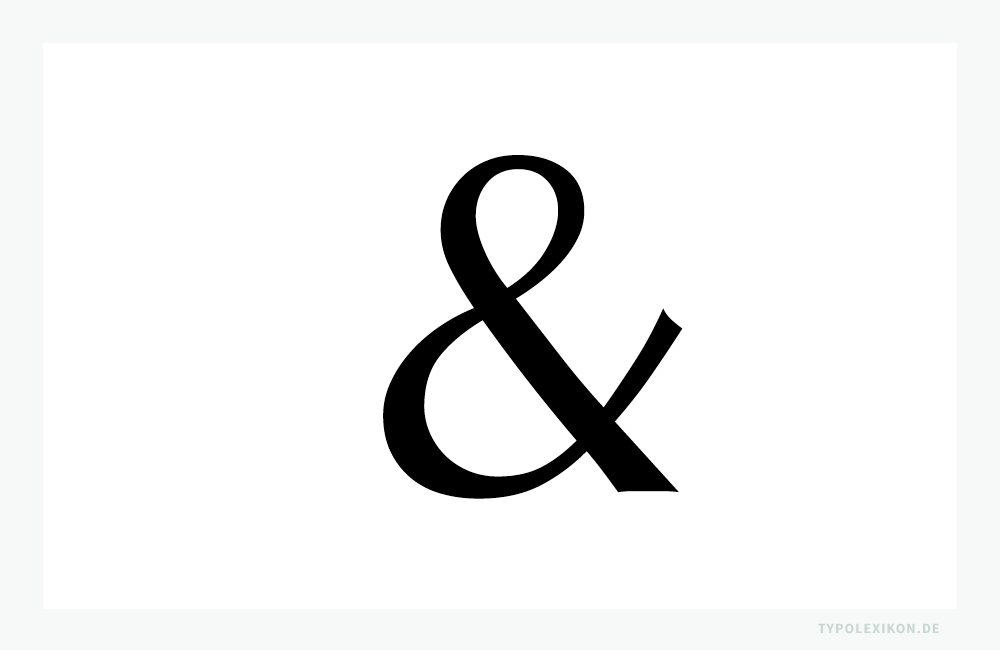
Da das &-Zeichen in der dt. Schriftsprache – im Gegensatz zur eng. 1) oder frz. 2) 3) 4) – nicht als grammatikalische Konjunktion (z.B. aber, denn, oder, und), sondern nur als Bindewort in Firmierungen (offiziell nur bei Firmendoppelnamen mit Eintrag ins Handelsregister) oder in der besonderen Rechtsform der Kommanditgesellschaft (KG) – der GmbH & Co. KG – verwendet wird, 5) wird es ab dem späten 19. Jh. auch als »kaufmännisches Und-Zeichen«, »Kaufmanns-Und«, »kaufmännisches Und« oder »Firmen-Und« bezeichnet. Das »&« sollte nicht mit der Kaufmannsligatur »@« (at-Zeichen) oder dem »+« (Pluszeichen) verwechselt werden.
Ursprung
Das &-Zeichen ist eine Buchstabenverschmelzung aus den Minuskeln »e« und »t«. Etymologisch rührt diese aus der lt. Konjunktion »et« für dt. »und«, »und tatsächlich«, »auch«.
Vermutlich entstand die &-Ligatur in ihrer heutigen Antiqua-Form als kalligrafische Abbreviatur mit den Minuskeln karolingischen (Karolingischen Minuskel) und humanistischen (Humanistica) Ursprungs, wobei die Epigraphik, die Paläografie und die Diplomatik bereits in vorrömischen Alphabeten erste Zeugnisse von Ligaturen und Abbreviaturen (Abkürzungen) dokumentieren.
In der Kalligrafie erfüllten Ligaturen bzw. Abbreviaturen primär die Aufgabe, schnell und ökonomisch zu schreiben, da u.a. Trägermaterialien wie Pergament bzw. später Papier sehr rar und kostbar waren. Sprachliche oder formale Aspekte kamen erst später hinzu (11./12. Jahrhundert). Ästhetische Aspekte in der Formgebung und Anwendung erst nach dem Manierismus. 6)
Generell ist es sehr schwer festzustellen, ob und ab wann eine Ligatur als originär oder als zusammengesetzt betrachtet werden muss. Das gilt auch für das &-Zeichen. Insbesondere, da in der europäischen Kalligrafie Ligaturen spätestens seit dem 1. Jahrhundert – z.B. in Form unterschiedlicher et-Zeichen – genutzt werden. Zu den ältesten noch angewandten Abbreviaturen zählt das et-Zeichen aus dem Zeichenrepertoire der Tironischen Noten von Marcus Tullius Tiro (um 103–4 v.Chr.), welches auch heute noch in Irland in unveränderter Form genutzt wird.
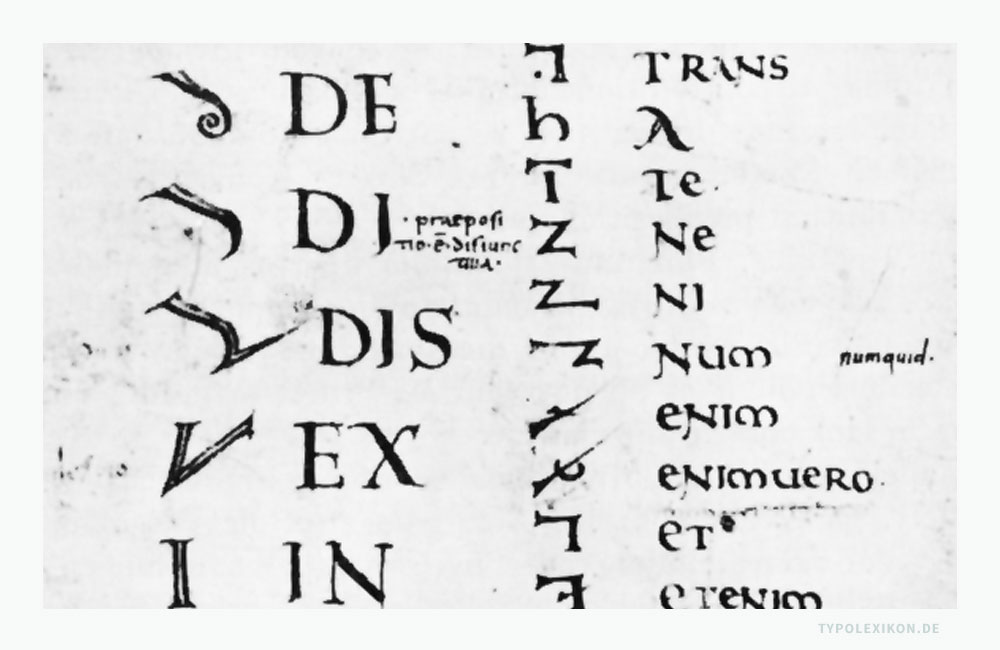
»Das &-Zeichen fast so alt wie die römische Schrift. Zwar kommt ein &-Zeichen weder in den altrömischen Inschriften noch in den monumentalen Majuskelhandschriften der Römer vor. Aber bereits 79 nach Christus begegnen wir in den flüchtigeren »graffiti«, schnell hingekratzten Inschriften, einer Ligatur et, die vielleicht als Urahn der et-Sippe angesprochen werden darf.«
In der dt. Fraktur-Typografie war das &-Zeichen über Jahrhunderte nicht üblich. Erst im Laufe der prosperierenden Industrialisierung und insbesondere mit Gebrauch von Antiqua-Druckschriften wurde das &-Zeichen ab dem späten 19. Jahrhundert als »ligaturische Abbreviatur« in Firmendoppelnamen – sowohl im Druckwesen als auch in der Schildermalerei – verwendet.
Orthographische Regeln
Die deutsche (und österreichische) Orthografie kennt – abgesehen vom »ß« (Eszett, Scharfes s) – keine Ligaturen. Dementsprechend finden sich im amtlichen Regelwerk zum Umgang mit dem &-Zeichen keine Vorgaben. In der Schweiz dto. 8)
Typografische Regeln
Im typografischen Schriftsatz haben sich nachfolgende Satzregeln etabliert.
Regel Nr. 1
Das &-Zeichen ist keine Alternative zum »+« (Pluszeichen) – bzw. auch nicht umgekehrt.
Beispiel:
Hinz & Kunz AGHinz + Kunz AG1 + 2 = 31 & 2 = 3
Regel Nr. 2
In dt. Fließtexten bzw. im geschlossenen Schriftsatz sollte das &-Zeichen nicht als Abkürzung für das Bindewort »und« verwendet werden, da es den Leseprozess spürbar erschwert (siehe Fixationen). Gleiches gilt für dspr. Titel und Überschriften (Headlines) sowie dspr. Marginalien und Fußnoten. 9)
Beispiel:
Die Eltern und ihre Kinder gehen in den Garten.Die Eltern & ihre Kinder gehen in den Garten.
Regel Nr. 3
Bei ausgeschriebenen Firmendoppelnamen und bei Rechtsformen von Unternehmen steht vor und nach dem &-Zeichen immer ein Leerraumzeichen. In der Mikrotypografie werden im traditionellen Sinn vor und nach dem &-Zeichen etwa zwei Drittel des normalen Abstandes gesetzt. 10)
Beispiel:
Bang & Olufsen Group Mustermann GmbH & Co. KG Maria Mustermann, Max Mustermann & Co. Grafikdesigner GbR Miele & Cie. KG Tiffany & Co.
Regel Nr. 4
Bestenfalls sollte ein Zeilenumbruch vor und nach dem &-Zeichen vermieden werden. Wenn eine Trennung unvermeidbar ist, kann das &-Zeichen am Ende der Zeile als auch am Anfang der neuen Zeile stehen. Die Entscheidung erfolgt nach ästhetischen Gesichtspunkten. Nach traditionellen Regeln steht ein abgetrenntes &-Zeichen am Anfang der neuen Zeile.
Sie waren Mitarbeiter einer Forschungsgruppe der Hinz & Kunz GmbH & Co. KG, die niemals sonntags freibekamen. Sie waren Mitarbeiter einer Forschungsgruppe der Hinz & Kunz GmbH & Co. KG, die niemals sonntags freibekamen.
| ↑10 | Quelle: Luidl, Philipp: Typografie, Herkunft, Aufbau, Anwendung. Schlütersche Verlagsanstalt und Druckerei, Hannover, 1984, ISBN 3–87706-212–1, Seite 45. |